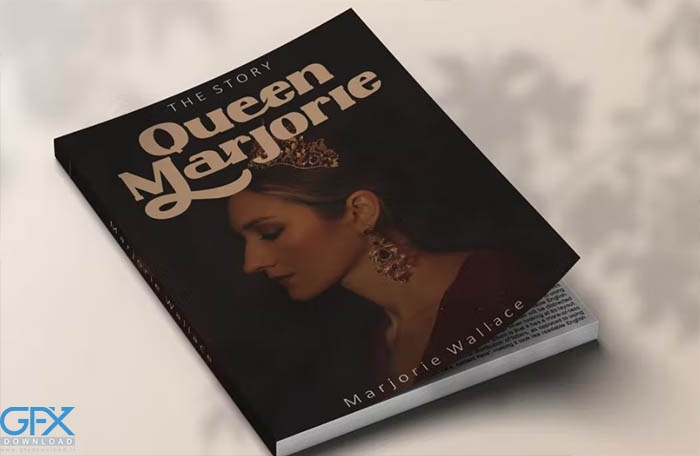
Heathfield یک فونت انگلیسی پررنگ به سبک قدیمی می باشد. یک فونت شیک که بافت ضخیم آن حال و هوای دهه 70 را به همراه دارد و سریف ها آن را کمی به حالت سنتی باز می گرداند. همراه با جایگزین ها و لیگاتورها، به ایجاد لوگوهای خیره کننده، نقل قول ها، پست های وبلاگ، پروژه های برندسازی، تصاویر مجلات، دعوت نامه های عروسی و موارد دیگر کمک می کند. برای دانلود فونت Heathfield با استایل وینتیج و قدیمی از جی اف ایکس دانلود به ادامه مطلب مراجعه کنید.
کاراکترهای جایگزین به چندین ویژگی نوع باز مانند Swash، Stylistic Sets، Stylistic Alternates، Contextual Alternates و Ligature تقسیم شدند. با استفاده از برنامه‌های هوشمند Open Type مانند Adobe Illustrator، Adobe InDesign، Adobe Photoshop Corel Draw X و Microsoft Word می‌توان به ویژگی‌های Open Type دسترسی پیدا کرد. این فونت انگلیسی از چند زبان نیز پشتیبانی می کند.